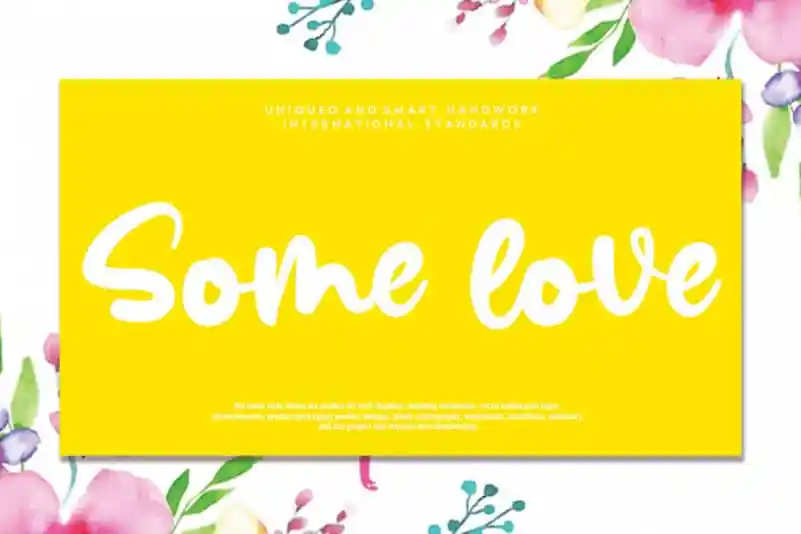
A Some Love Script Font é uma elegante fonte escrita à mão que captura a essência do estilo serifa ao mesmo tempo que traz uma sensação contemporânea e moderna. Perfeita para quem busca um toque diferente e sofisticado em seus projetos, ela mantém sua classificada influência da calligrafia enquanto se atualiza constantemente. A Some Love Script Font é uma fonte escrita à mão que vai cativar seu coração, ajudando-a a dar vida aos mais belos projetos digitais. Com certeza será um dos seus favoritos em sua biblioteca de fonts.